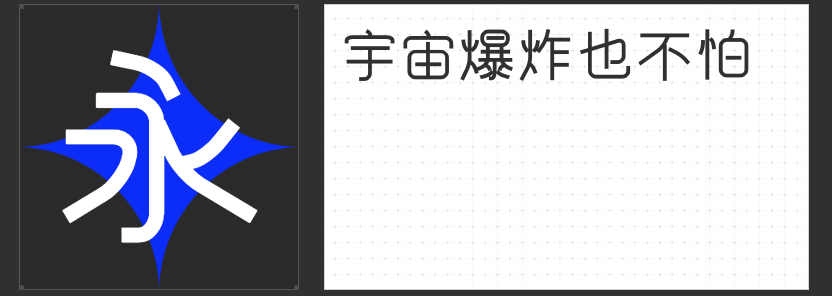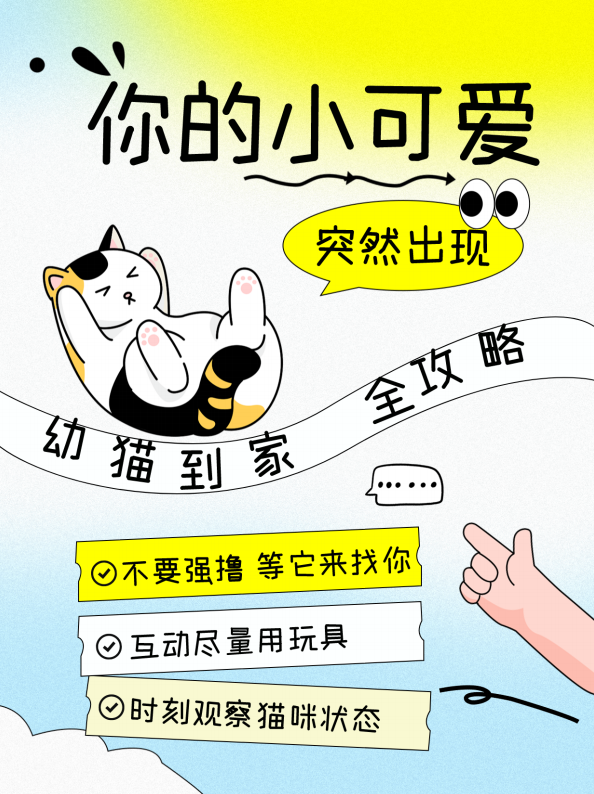
圆润百变,字里乾坤:四款圆体字体推荐
圆体字体,以其圆润柔和的笔画、饱满可爱的字形,一直深受设计师和大众的喜爱。今天,就为大家推荐四款各具特色的圆体字体,带你领略圆体字的多彩魅力。
一、励字粗圆简繁:方正饱满,端庄大气
如果你在寻找一款醒目大气的圆体字体,那么励字粗圆简繁绝对是你的不二之选。这款字体字面较大,结构方正饱满,笔形柔和,笔画较粗,整体给人一种端正大方、稳重大气的感觉。无论是用于标题设计,还是海报宣传,都能轻松吸引眼球,营造出强烈的视觉冲击力。
二、励字细圆简繁:清瘦纤细,简约精致
与励字粗圆简繁的厚重感不同,励字细圆简繁则显得更加清瘦纤细。这款字体比黑体更细,没有衬线装饰,字面呈正方形,一笔一画都清晰可见。撇捺等笔画不尖,字形端庄,笔画横平竖直,全部一样纤细,结构醒目严密,给人一种简约精致、清新淡雅的感觉。非常适合用于正文排版、书籍印刷等需要长时间阅读的场景。
三、 高手庆科可爱体:灵动活泼,趣味十足
想要为你的设计增添一份趣味和活力?那就试试高手庆科可爱体吧!这款字体结构灵活,具有手写感,笔画整体使用直线设计,笔画端点和折笔处都采用了圆角的处理方式,横竖笔画视觉等粗,竖弯钩、内部空间紧凑的竖钩采用了去钩的处理方式,让字型更加干净简洁。字体内部留白均匀,易于阅读,整体给人一种灵动活泼、趣味十足的感觉,非常适合用于儿童读物、卡通漫画、游戏界面等场景。
四、励字多元宇宙简:圆润柔和,未来感十足
最后一款推荐的是励字多元宇宙简,这款字体将圆体字的特点发挥得淋漓尽致。它将折笔处变为圆弧形状,圆润且不失力度,笔画粗细均匀,字形紧聚,但不失美感,感觉更加柔和、舒适。同时,这款字体还融入了一些未来感的设计元素,给人一种科技感十足的感觉,非常适合用于科技类产品宣传、未来主题设计等场景。
总而言之,这四款圆体字体各有千秋,能够满足不同场景的设计需求。希望这篇文章能帮助你找到心仪的字体,为你的设计增添一份独特的魅力!